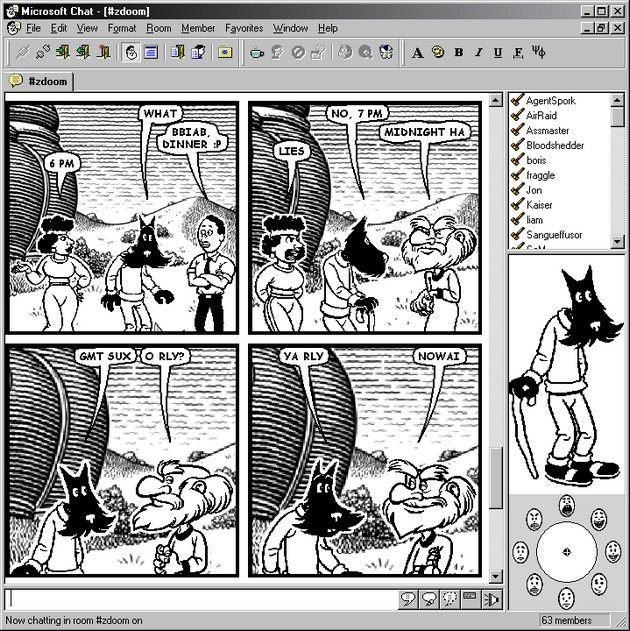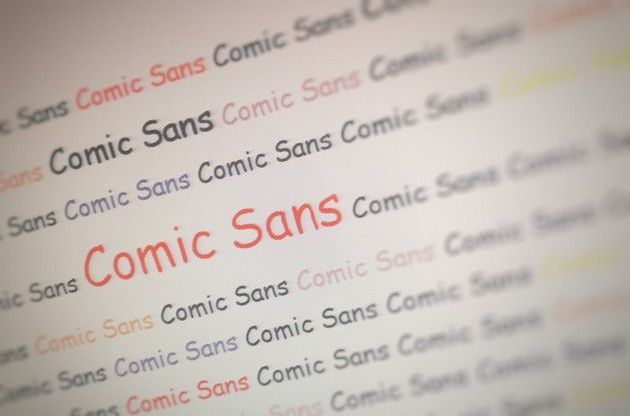
„Dwadzieścia lat temu stworzyłem najlepszy font na świecie” – oświadczył Vincent Connare podczas tegorocznej edycji konferencji Wired. Nie cała londyńska publiczność zgodziła się jednak z tym stwierdzeniem. Język wypychający policzek mówcy także pozwalał wierzyć, że autor nie mówi tego po to, żeby się przechwalać. Właściwie to całkiem zrozumiałe, Connare mówił bowiem o bardzo dobrze znanym foncie, którego każde użycie – przynajmniej według miejskich legend – zabija gdzieś na świecie jednego kotka. Dwa słowa, które przyprawiają o ból głowy grafików i estetów w ogóle: Comic Sans.
Po sześciu latach spędzonych na stanowisku starszego projektanta CAD w Agfa, w 1993 roku Vincent Connare dołączył do Microsoftu jako menedżer ds. programów. Gigant przygotowywał się wtedy do wypuszczenia na rynek swojego rewolucyjnego systemu Windows 95. – „To była największa informatyczna premiera w tamtych czasach. Jestem zaszczycony, że mogłem być tego częścią. To był początek oprogramowania użytkowego – to było bardzo ekscytujące” – wspomina Connare.
Connare mówi, że gdy dołączał do Microsoftu, w firmie panował silny duch przedsiębiorczości. – „Mówili nam, że jesteśmy najlepsi na świecie w tym co robimy. Tak więc zamiast czekać na to, co szef każe nam zrobić, sami mogliśmy powiedzieć mu, co chcielibyśmy zrobić. To było kluczowe. Każdy zastanawiał się nad tym, co najlepszego może w danej chwili zrobić. Wszyscy byliśmy przedsiębiorczy i wszyscy myśleliśmy w tych kategoriach”.
Nie wiadomo czy miało to bezpośredni wpływ na pojawienie się Comic Sans, ale z pewnością jakiś wpływ miało. W początkowych etapach działalności Microsoft stworzył wiele konsumenckich programów – wśród nich był Creative Writer, coś jak prototyp Worda dla dzieci z wieloma fontami, efektami, clipartami itd. Potem menedżerowie ds. programów zapukali do biura szefostwa i zaprezentowali oprogramowanie o nazwie Utopia, które później przerodziło się w Microsoft Bob – bardziej przyjazną dla użytkownika powłokę na system operacyjny Windows.
Sam Microsoft Bob nie został zbyt ciepło przyjęty przez użytkowników. To jednak jest bez znaczenia dla tej historii. Connare został pewnego dnia zapytany, co sądzi o fontach w tej powłoce. – „Zobaczyłem tego psa, który mówił w Times New Roman i pomyślałem «to nie tak powinno wyglądać». Lubię komiksy, zbieram komiksy i ich bohaterowie nie mówią w Times New Roman. Spojrzałem na kilka egzemplarzy w swojej kolekcji i zdałem sobie sprawę, że w większości wykorzystują one pismo odręczne” – odpowiedział.
Pewnie domyślacie się co było dalej. Wejdźmy jednak głębiej. Okazuje się bowiem, że główne inspiracje dla Comic Sans były dwie – pochodziły z komiksów Mroczny Rycerz Powraca i Watchmen. – „Watchmenowi najbliżej było do fontu, więc wpatrywałem się w literki i powoli, za pomocą myszki przenosiłem jedną po drugiej na ekran monitora, starając się uzyskać zadowalający efekt” – wspomina Connare. – „To nie musiało być idealne. Byłem gotowy powtarzać ten proces tak długo, aż stworzę coś co przypominało, ale nie kopiowało, pisma Dave’a Gibbonsa. Chciałem zrobić coś… innego. Chciałem, by wyglądało to jak pismo odręczne”.
Jak się okazało, Comic Sans ostatecznie nie trafił do powłoki Microsoft Bob. Pojawił się za to w programie 3D Movie Maker, który także tworzony był przez oddział Microsoft Kids i który pozwalał animować trójwymiarowe postacie z kreskówek, dodawać efekty dźwiękowe i wizualne oraz okraszać „dzieło” podpisami. Później font znalazł się w programie Microsoft Comic Chat, który był graficznym komunikatorem internetowym. Wreszcie Comic Sans dostał się do systemu Windows 95 i stał się jednym z głównych fontów domyślnych w programach Internet Explorer oraz Microsoft Publisher.
Comic Sans osiągnął na przestrzeni lat status fontu niemal kultowego. Przeważnie jest wyśmiewany, ale raczej w pobłażliwym sensie, a fakt, że pomimo tak wielkiej niechęci, Comic Sans nigdzie się nie wybiera, mówi chyba sam za siebie.
„Ludzie często mnie pytają «kiedy jest dobry moment, aby użyć Comic Sans?». Cóż, CERN wykorzystał ten font, aby pochwalić się odkryciem bozona Higgsa i w żaden sposób ich to nie zabolało” – dodał z uśmiechem na ustach Vincent Connare.